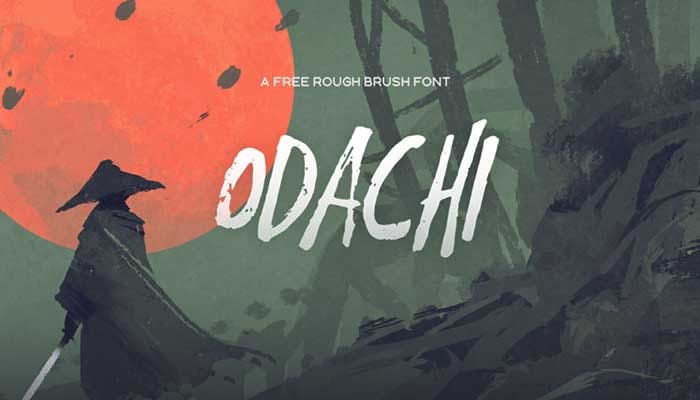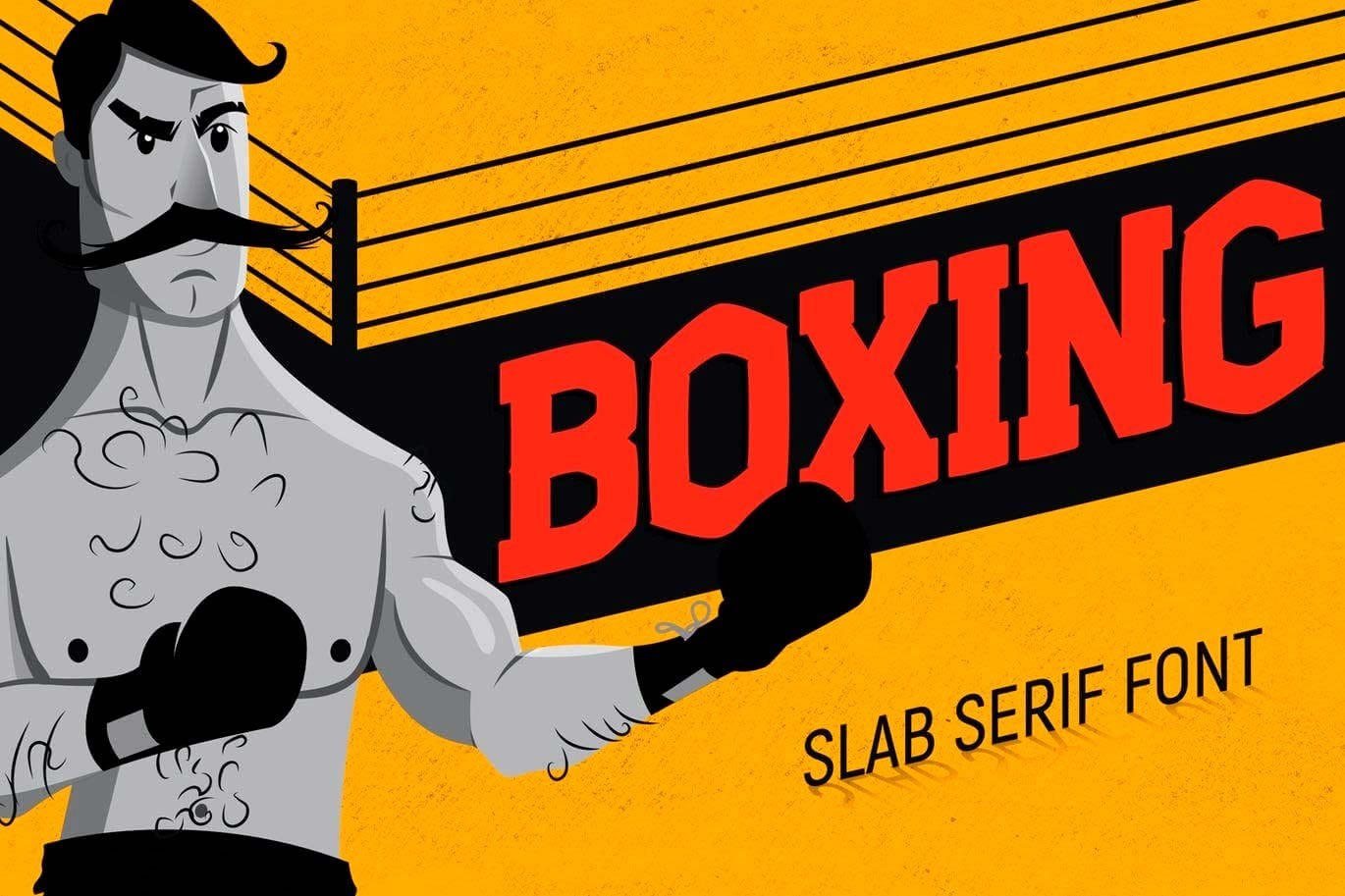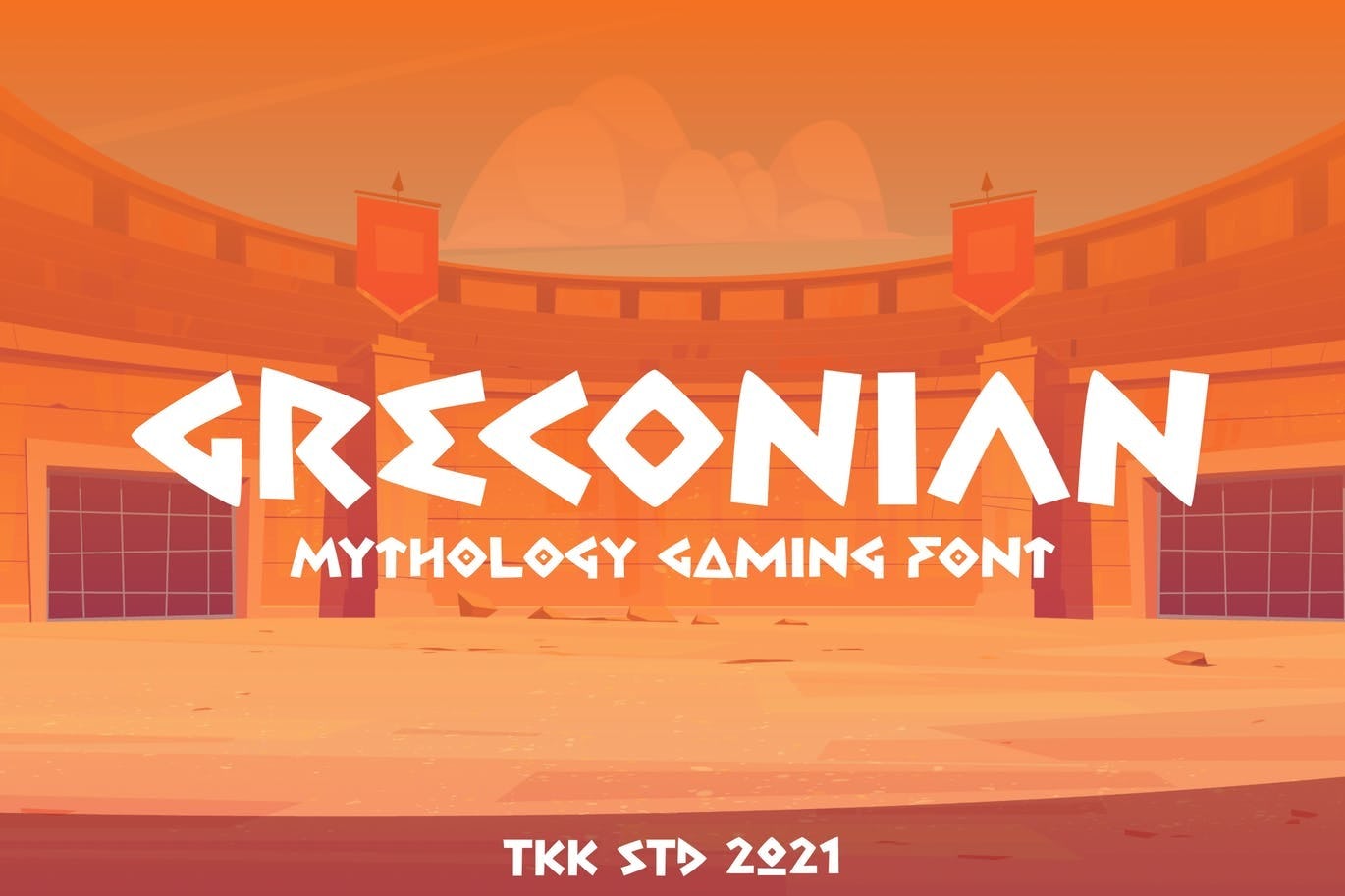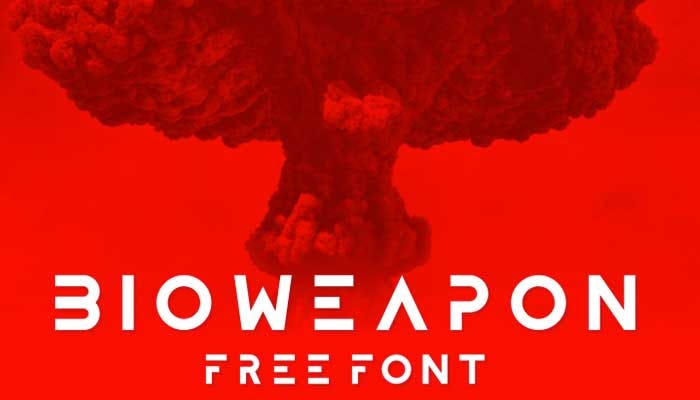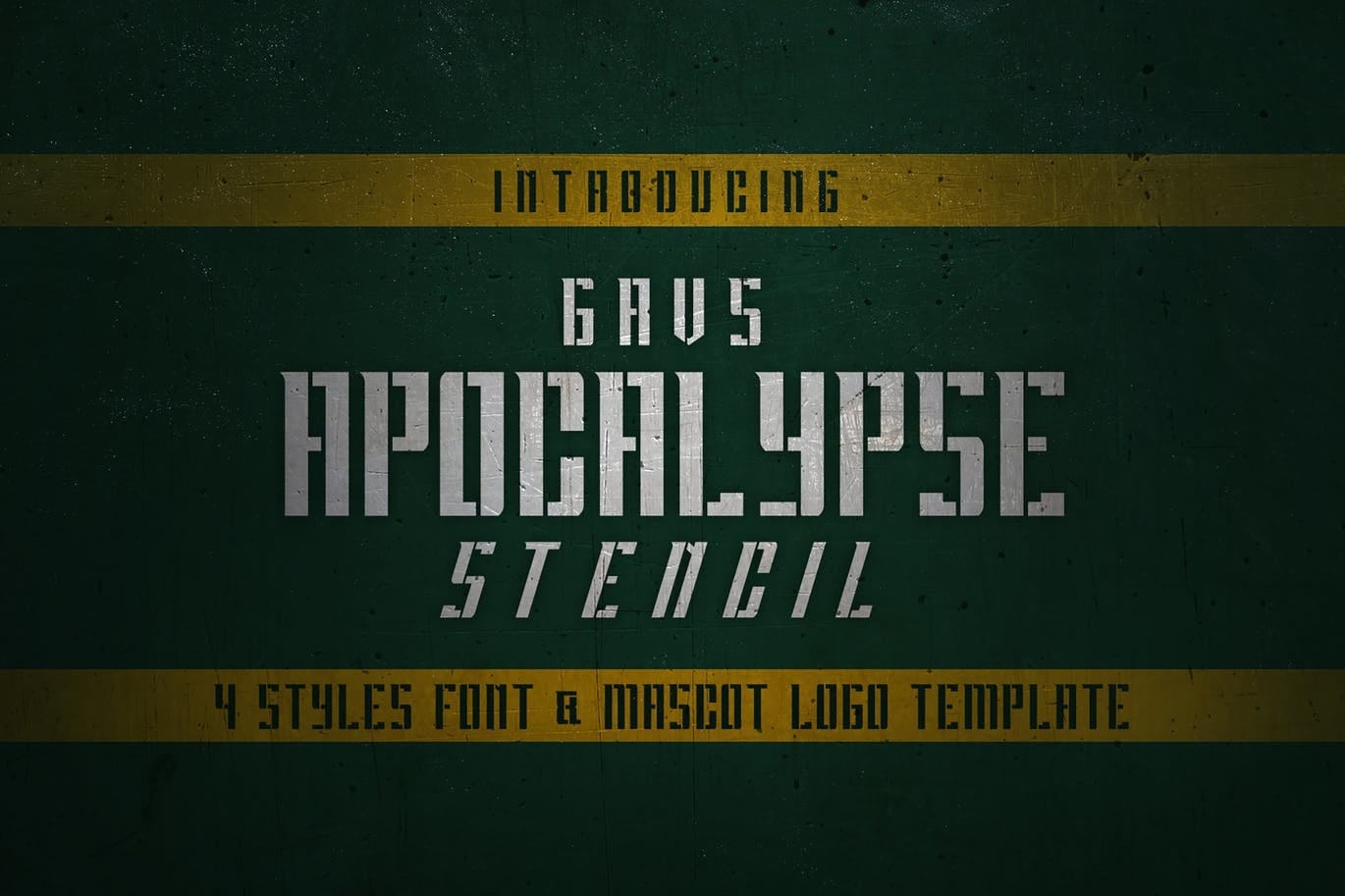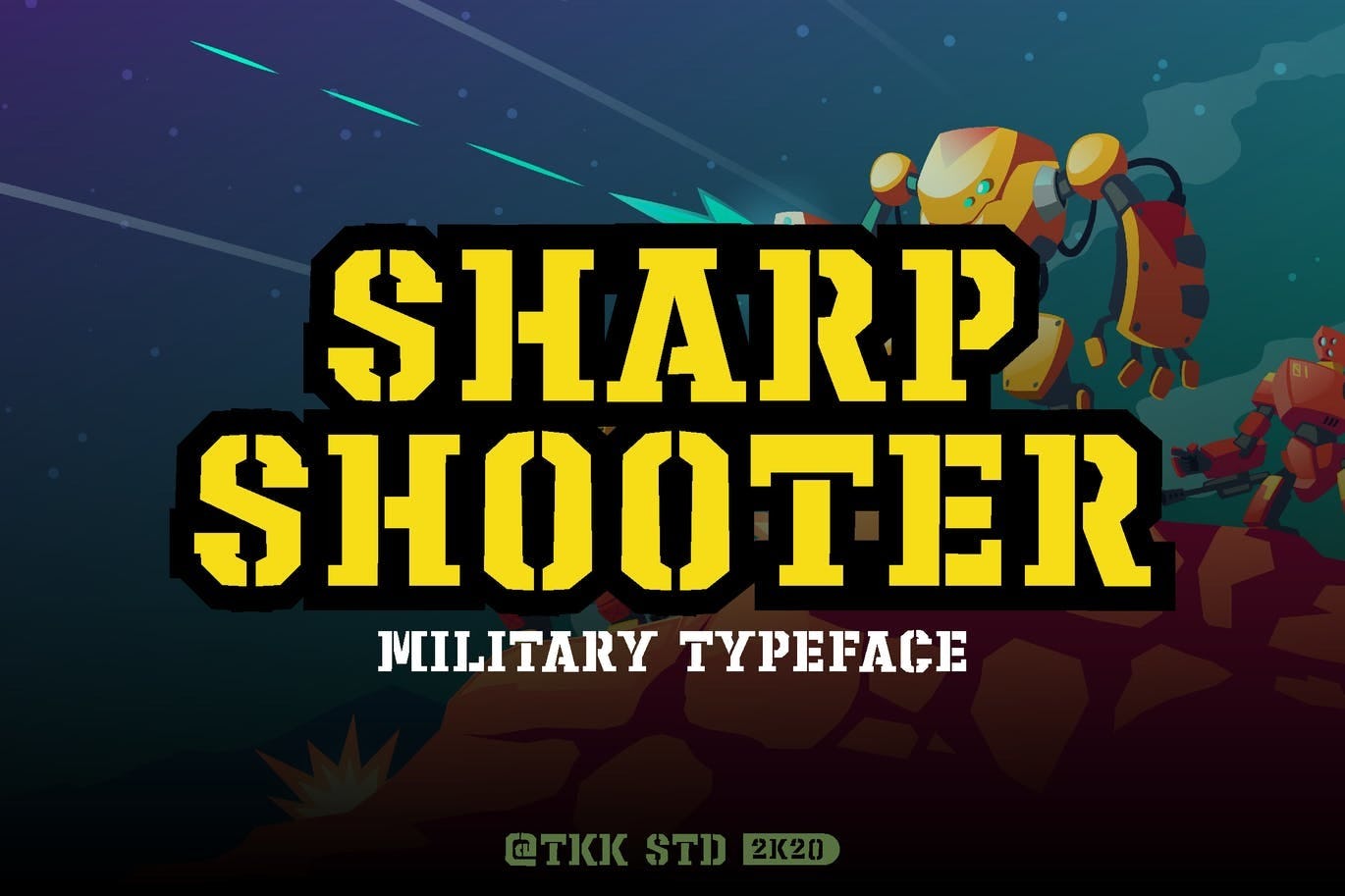
¿Te interesa conocer tipografías para videojuegos para decorar tus trabajos o para crear mensajes increíbles? ¿Eres fanatico de los estilos retros, modernos o pixeleados? Definitivamente, a todos en algún momento nos ha llamado la atención algún videojuego en la infancia y, sobre todo, te aseguro que hasta hoy puedes distinguir los tipos de letras de cada uno de tus favoritos.
Ya sean videojuegos antiguos como las primeras Nintendo, o videojuegos actuales como la Playstation o Xbox, todos de alguna manera han logrado cautivar a millones de personas.
¡Te contamos que estás de suerte! En el artículo de hoy, haremos un viaje en el tiempo. No solo recordaremos buenos juegos de video que marcaron cada época, sino destacaremos las fabulosas tipografías para videojuegos que, hasta la actualidad, son distintivas de cada género.
¡Mucho ojo que ya empieza el juego!
¿Qué son las tipografías para videojuegos?
Las tipografías son fuentes o estilos de letra que se utilizan en la caligrafía. Si nos trasladamos al terreno de los videojuegos, existen ciertas tipografías que son comunes, dependiendo del género. Entre los más conocidos tenemos las tipografías de juegos retro o arcade, disparos, combates, históricos, entre otros.
Aunque no lo creas, la tipografía en los videojuegos es un elemento muy importante, ya que suele ser de las primeras cosas que vemos. Entonces, según explica el artista conceptual, Pablo Olivera, en el curso online de Ilustración conceptual para cine y videojuegos, uno de los detalles finales (aunque no menos importantes) en la creación de videojuegos es la tipografía, la cual debe ir de acuerdo al concepto del juego y, a su vez, llamar la atención del consumidor.
Tipografías para videojuegos arcade
¿Sabes qué es arcade? Es un término que proviene del francés y se utilizó en Estados Unidos para designar las primeras máquinas de videojuegos en los 80’s. ¡Sí, las maquinitas! Como el término es tan versátil, también se usó para las tiendas de videojuegos.
Si bien no hay un registro exacto de cuál fue el primer videojuego, se sabe que los gráficos de aquella época eran diseñados a base de píxeles, también conocido como píxel art. En la actualidad, existen videojuegos que han copiado este estilo antiguo, como, por ejemplo, el famoso “Minecraft”.
Pero, ¿tienes idea de qué es un píxel? Se trata de un pequeño cuadro de color que, al agruparlo, conforma una imagen. Por ejemplo, según relata el portal de noticias El Universal, Pacman fue uno de los primeros juegos de arcade en los que se vieron este tipo de gráficos para videojuegos.
¿Sabías que los primeros videojuegos tenían una matriz de 8x8 píxeles? Por eso, los desarrolladores de esa época no podían ser tan creativos al momento de hacer las tipografías para videojuegos.
¡Menos mal hay una constante evolución de los videojuegos! Ahora podemos disfrutar de varias tipografías con diferentes efectos. ¿Quieres descubrir cuáles son? ¡Sigue leyendo!
¡Antes de continuar! Algo súper importante que debes tener en mente es que, por más que te gusten nuestras tipografías para videojuegos, solo debes usar máximo dos. De lo contrario, puedes saturar el diseño de tu proyecto. Ahora sí, ¡sigamos con nuestros descubrimientos!
Game over font
Otro aspecto que debes tener en cuenta como diseñador de videojuegos es que los tipos de tipografía que vayas a utilizar deben ser legibles para mejorar la experiencia de usuario.
En este caso, te recomendamos Game over font porque es uno de los mejores ejemplos de pixel art en los videojuegos. Eso sí, úsala para cortos anuncios en el juego, pero no para las leyendas.
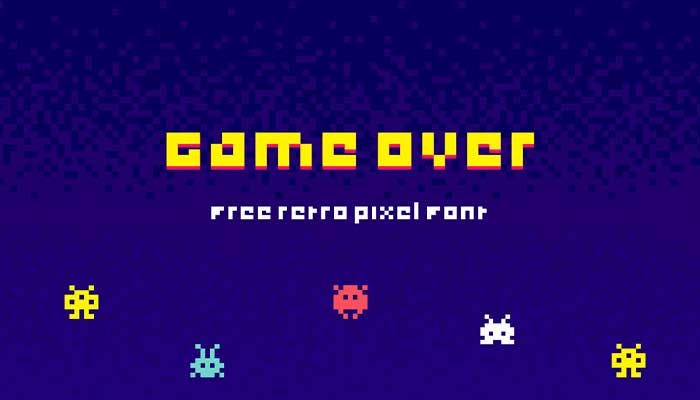
Mister Pixel Font
¡No podemos evitarlo! Uno de nuestros géneros de videojuegos favoritos es el arcade. Por eso, esta tipografía nos llama mucho la atención. A diferencia de Game over font, nos encanta el estilo retro tan marcado que tiene. ¡Gracias Christophe Badani por crearla!
Arco Font
Si estás diseñando una pieza gráfica en la que desees transmitir sensaciones relacionadas a la diversión y la alegría, Arco Font es la tipografía que necesitas.
Es ideal para títulos, logos y es adecuada para un videojuego dirigido a un público infantil.
Gomawo
Si buscas un estilo arcade con ciertos toques modernos, una de las mejores tipografías para videojuegos de este género es Gomawo. No tiene demasiados caracteres para varias lenguas, pero es una increíble opción para darle un nuevo aire a tu proyecto.
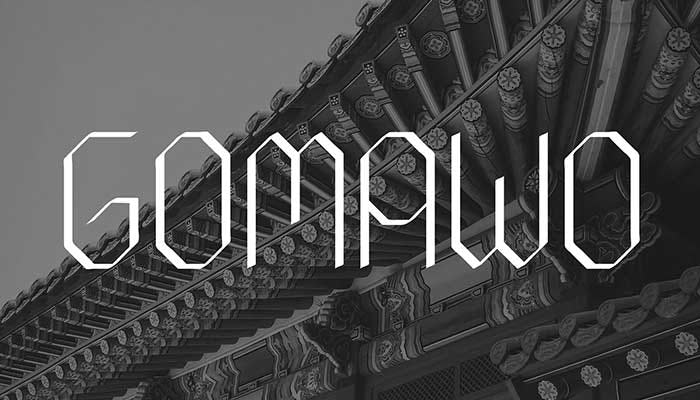
Retro Videogame Font and Characters
Siguiendo con esta lista de tipografías para videojuegos arcade, traemos esta plantilla con temática clásica estilo Atari. Si eres de la vieja escuela, en algún momento de tu vida has disfrutado jugar estos juegos repetitivos, pero muy innovadores para la época.
Su tipo de letra pixelado, como si fuera extraído del mismo videojuego de la década de los 80, sin duda, podrá destacar en cualquier pantalla. Además, te la recomendamos en esta lista de tipografías para videojuegos, porque cuenta con 17 figuras arcade para darle vida a tus mensajes.